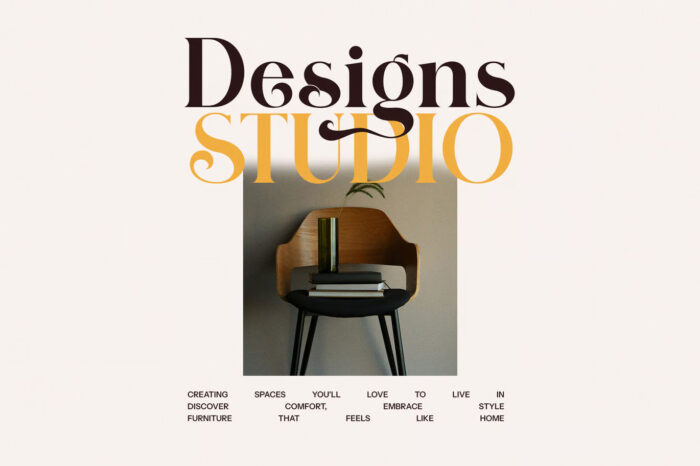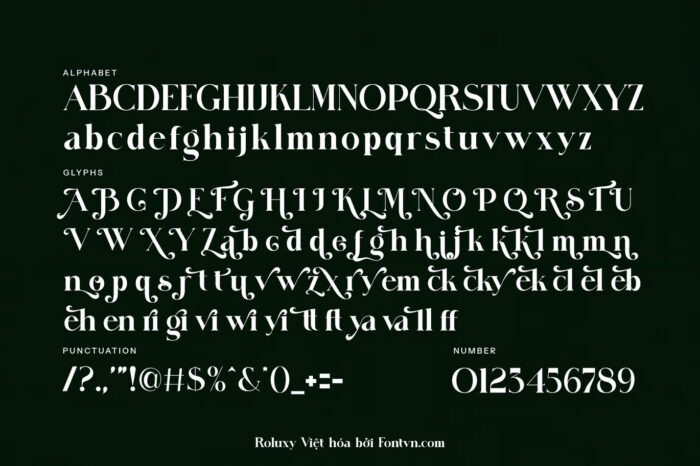
DVN Roluxy Việt hóa – Font chữ Logo đẳng cấp và sang trọng
“Roluxy” là một font chữ mang phong cách hiện đại, tinh tế và sang trọng. Với các đường nét uốn lượn nhẹ nhàng và sự cân đối, font này tạo ra cảm giác thanh lịch và quý phái. Sự kết hợp giữa các đường nét dày và mảnh cùng những điểm nhấn tinh tế như các nét cong mềm mại làm tăng thêm sự uyển chuyển và bắt mắt cho thiết kế.
Font chữ này rất phù hợp cho các thương hiệu thời trang cao cấp, mỹ phẩm, hoặc những sản phẩm muốn truyền tải thông điệp về sự đẳng cấp và phong cách. “Roluxy” cũng lý tưởng cho các thiết kế in ấn như thiết kế Logo sang trọng, thiệp mời, tiêu đề tạp chí, hoặc các chiến dịch quảng cáo đòi hỏi sự tinh tế trong từng chi tiết. Nhìn chung, “Roluxy” đem lại một cảm giác quý phái và chuyên nghiệp, dễ dàng thu hút ánh nhìn trong các dự án thiết kế cao cấp.
Font có hỗ trợ Ligature và Glyphs giúp bạn tạo ra hiệu ứng chữ đẹp mắt và thay thế các ký tự, xem hướng dẫn dùng Ligature và Glyphs tại đây